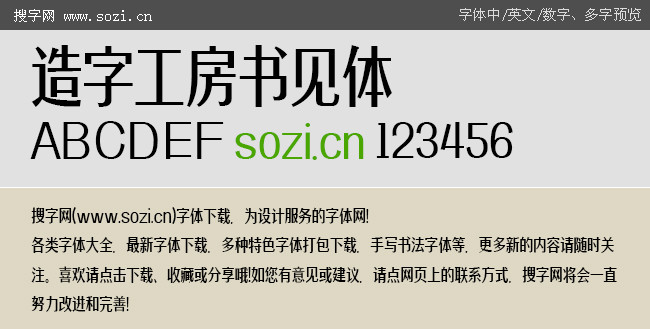
造字工房書見體
搜字網(wǎng)給大家提供一款造字工房書見體中文字體下載,造字工房書見體字形修長(zhǎng),體勢(shì)勁媚,骨力道健,其風(fēng)格瘦勁不失柔美之感,雅致簡(jiǎn)潔。字形柔中帶銳,處處體現(xiàn)一種靜態(tài)美感。適用于海報(bào)設(shè)計(jì),網(wǎng)頁(yè)廣告,書籍封面,包裝設(shè)計(jì)等應(yīng)用。(本字體為個(gè)人非商用版,如需要商用請(qǐng)聯(lián)系官方購(gòu)買版權(quán))